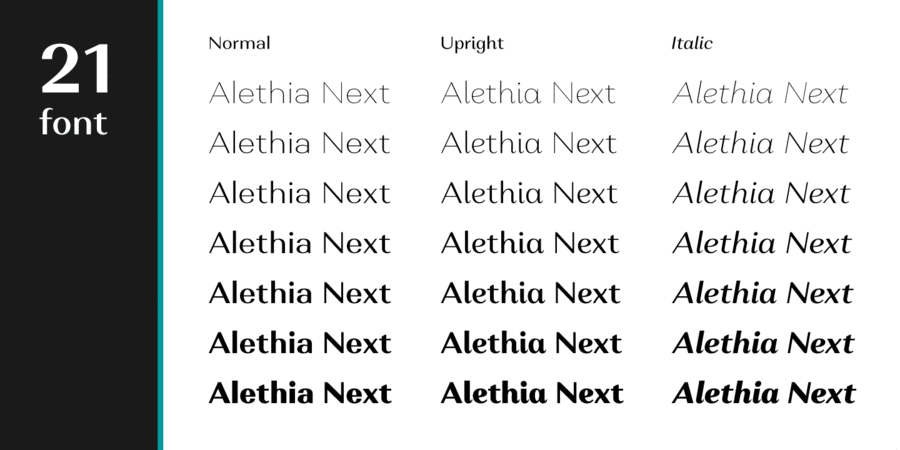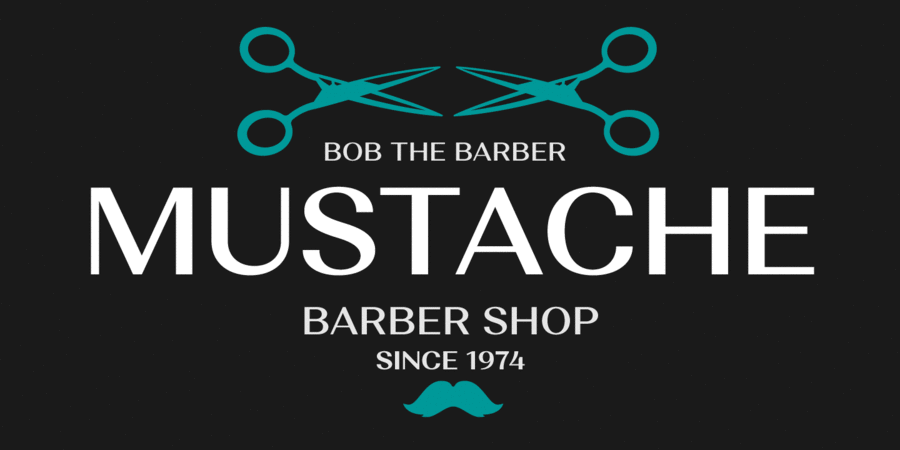
Alethia Next – це ґротеск з високою контрастністю в усіх накресленнях. Він призначений для акцидентного використання в різних редакційних проектах, таких як журнали й корпоративні брошури, як гротескова пара до сучасних антикв. Сімейство має 7 ваг жирності + курсиви + прямі курсиви. Кожне накреслення підтримує безліч мов на кирилиці та латиниці, включно з болгарськими грефемами. Гарнітура містить OpenType фічі, такі як лігатури, капітель і численні альтернативні гліфи. Alethia Next розробив Олег Ліщук у 2019 році.
Асоціації з сімейством шрифтів Alethia NextОсобистість і характер гарнітури:
тонкий, худий, витончений, холодний, делікатний, чистий, легкий, прохолодний, свіжий, модний, якісний, культурний, добірний, благородний, гармонійний, елітний, дорогий, розкішний, красивий, майстерний, знаменитий, оригінальний, багатий, сучасний, міський, прозорий, дротяний, точний, гладенький, твердий, чіткий, різкий, прямий, статичний, естетичний, художній, освічений, елегантний, комільфо, джентльменський, сексуальний, ефектний, формальний, яскравий, виразний, пафосний, монументальний, серйозний, авторитетний, надійний, важливий, гордий, діловий, стійкий, сталевий, артистичний, ексцентричний, претензійний, стабільний, впевнений, переконливий, сильний, апетитний, урочистий, помітний, гнучкий, ритмічний, приємний, ввічливий, пластичний, грайливий, рівний, хіпстерський, манірний, тактичний